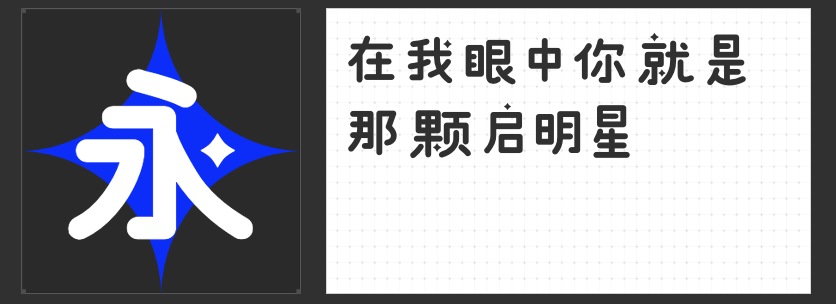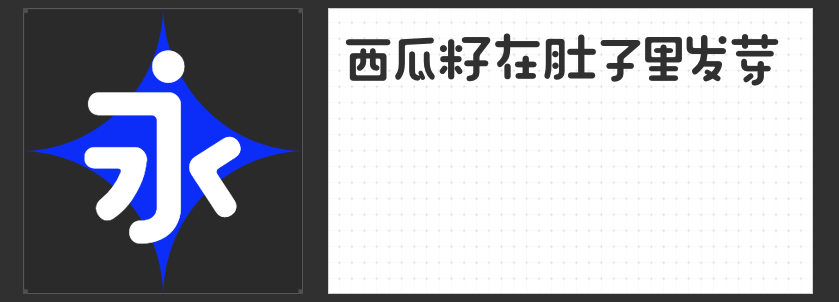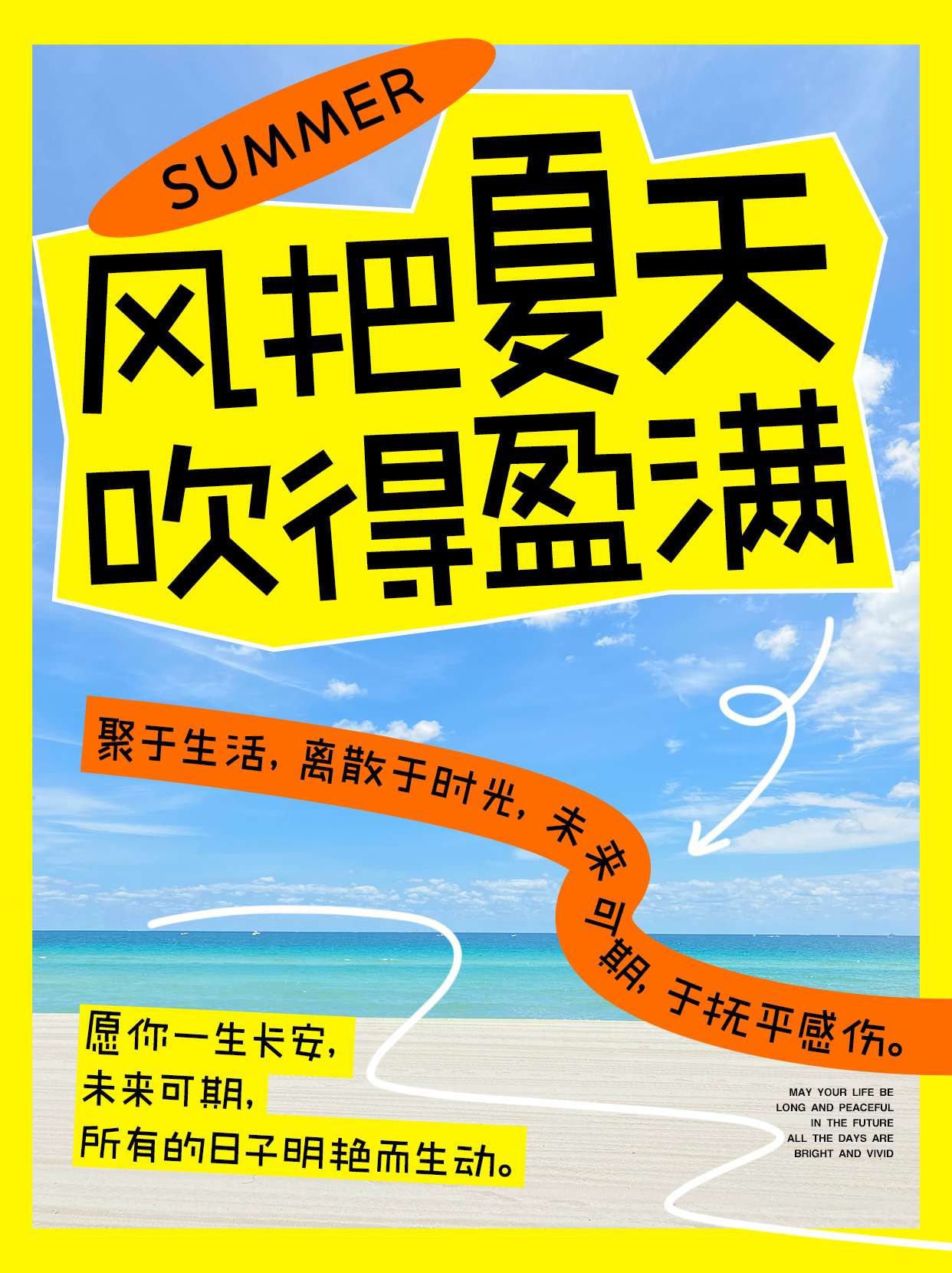
二次元世界里的字体宝藏:四款不可错过的创意字体推荐
在二次元文化的浪潮中,字体设计也迎来了属于它的璀璨时刻。今天,就让我们一起探索四款专为二次元爱好者打造的独特字体,它们不仅各具特色,还能为你的作品增添无限创意与个性魅力。
一、字恋狂漫野 鸣风:手写韵律的直线演绎
“字恋狂漫野 鸣风”以其独特的手写感直线设计,在二次元字体中独树一帜。它巧妙地在结构中融入张弛有度的美感,布白空间通透,字型大小错落有致,如同跳跃的音符,赋予版面鲜活的生命力。笔画简洁而不失灵动,去钩处理与“断开”设计,让每一个字都显得既现代又不失趣味,是追求版面活跃度的绝佳选择。
二、励字造桃气圆 准粗:圆润手写的温柔力量
如果你偏爱圆润可爱的风格,“励字造桃气圆 准粗”将是你的不二之选。这款字体以手写感圆体为基础,字型上松下紧,重心略低,展现出一种轻松愉悦的氛围。圆润饱满的笔形,搭配内外圆角兼备的折笔设计,以及巧妙融入的圆形元素,让整体风格更加轻快活泼。笔画间的“断开”处理,更添一份灵动与透气感,让阅读成为一种享受。
三、高手字斋哥特体Pro:灰度之巅的哥特风情
对于喜爱哥特风格的创作者来说,“高手字斋哥特体Pro”无疑是展现个性与深度的理想字体。其高灰度设计,让每一个笔画都充满了力量与神秘感,仿佛能直击心灵深处。这款字体不仅保留了哥特字体的经典元素,更在细节上进行了精心打磨,确保每一次使用都能带来震撼的视觉效果。
四、高手兵克星耀体:星辰大海中的闪耀之星
最后,让我们来认识“高手兵克星耀体”。这款字体虽未在本文中详细展开,但它以其独特的星辰设计理念和耀眼的视觉效果,在二次元字体中同样占有一席之地。无论是用于标题还是装饰性文字,都能瞬间吸引眼球,成为作品中的亮点。
这四款字体,每一款都是二次元文化与传统字体设计的完美融合,它们不仅丰富了我们的视觉语言,更为创作带来了无限可能。不妨在你的作品中尝试它们,让文字也成为传递情感与故事的重要媒介吧!